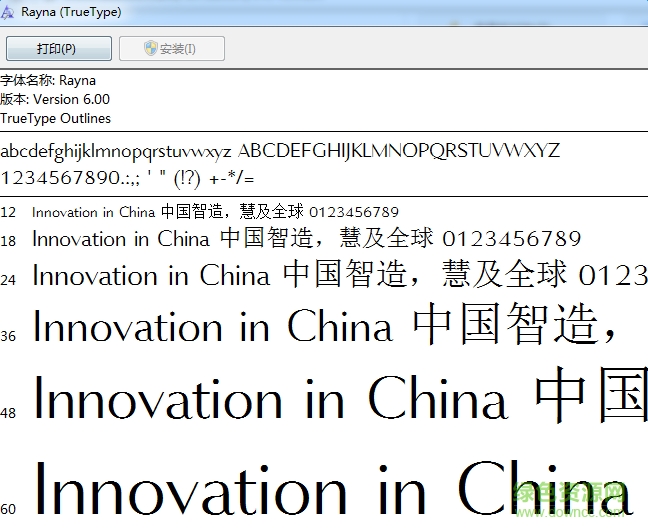
Rayna字體是一款漢儀西文字庫(kù)中的個(gè)性英文字體,該字體可以廣泛應(yīng)用于廣告設(shè)計(jì)、宣傳海報(bào)、ppt、影視制作以及任何使用文字的領(lǐng)域,有需要的朋友可以免費(fèi)下載收藏。
Rayna字體是漢儀西文字體庫(kù)中的一款個(gè)性英文字體,該字體非常端莊大方,適用于多個(gè)方位,有需要的朋友可以來(lái)綠色資源網(wǎng)下載使用!